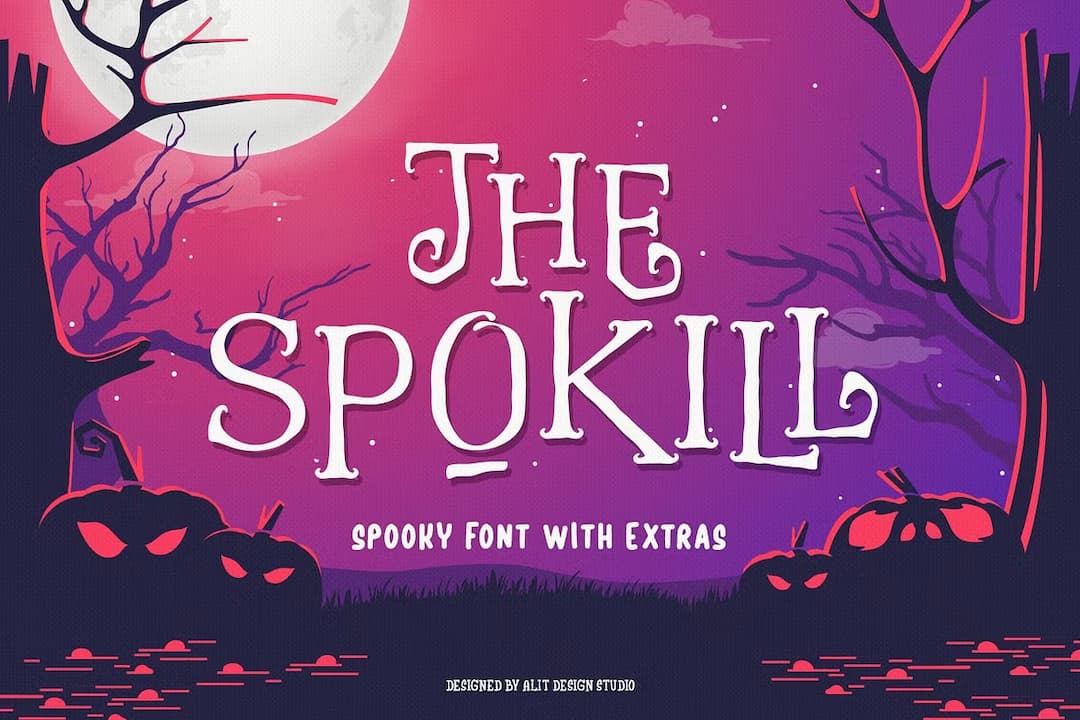
The Spokill
はい本日ハロウィーンということでこちら。アウトラインガタガタ、グリフも不揃いのよくあるタイプのディスプレイローマン。ぐりぐりカールした不気味なスワッシュオルタネートとリガチャーがかなり豊富で、簡素なものが多いこの手の書体としてはなかなか使い勝手が良い。さらにはイラストアイコンが入ったフォントも別にあり、この点でも素晴らしいと思う。大文字だけかと思いきや小文字もあるのでご安心を。ただ当日に紹介してどうすんねんという気は自分でもする(笑)。皆さん楽しいハロウィーンを。